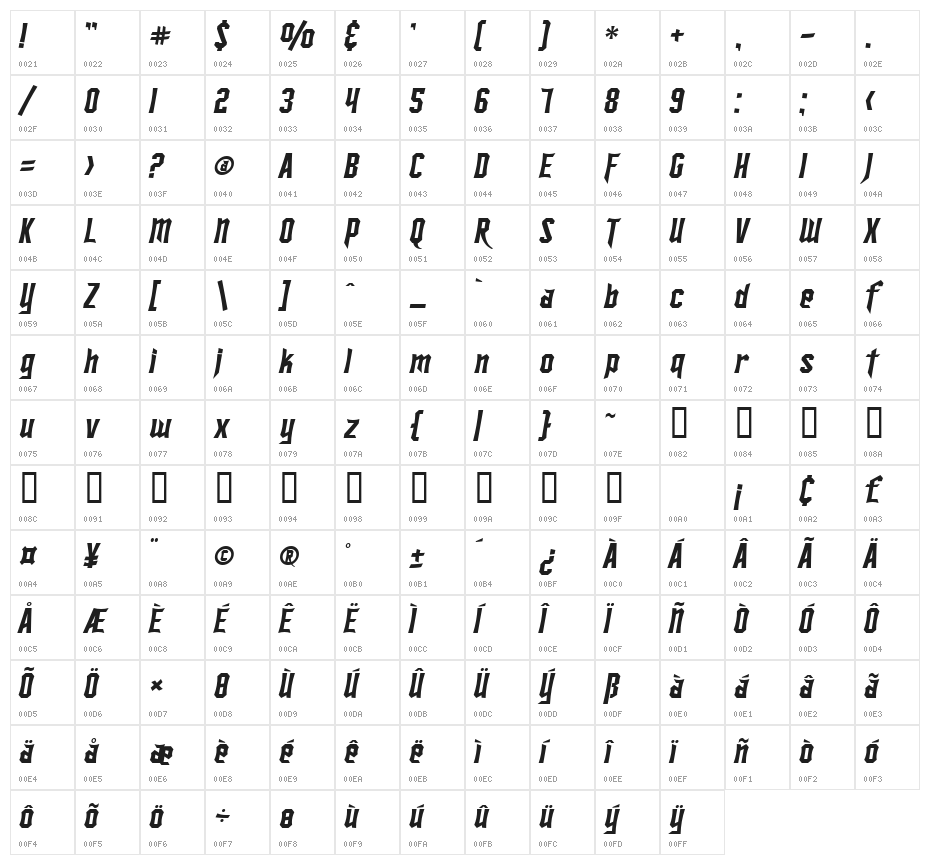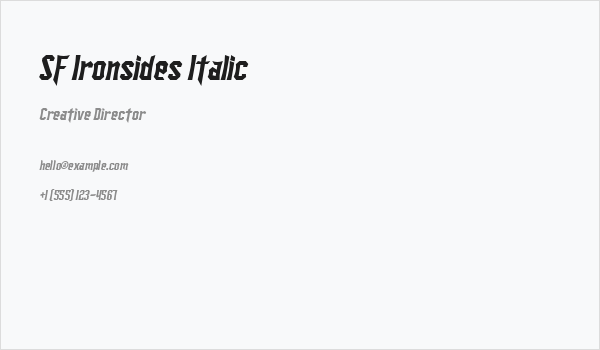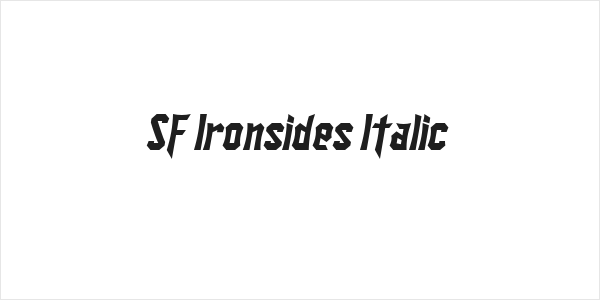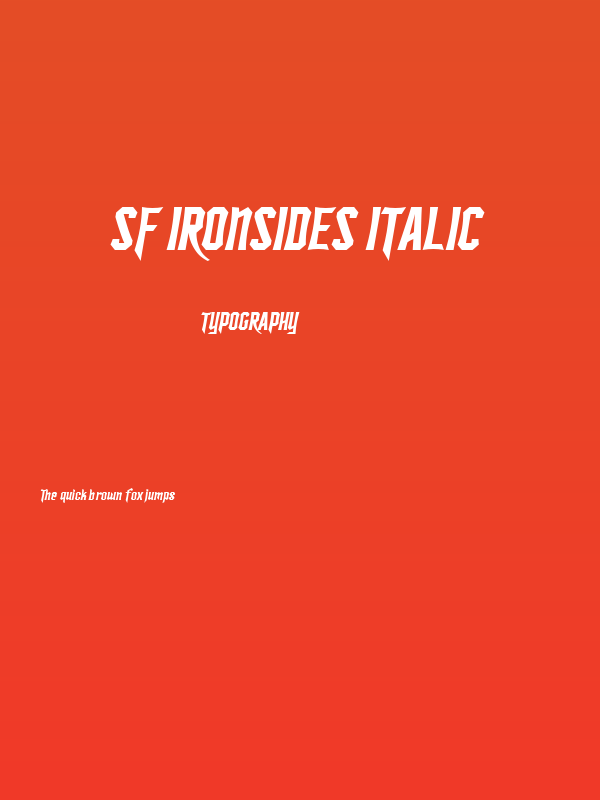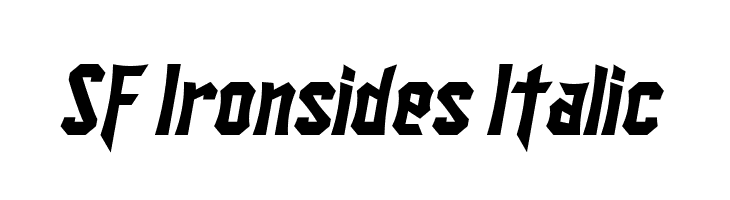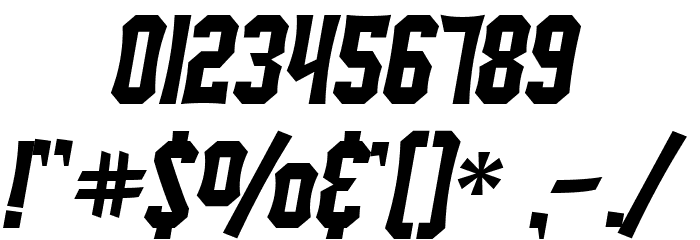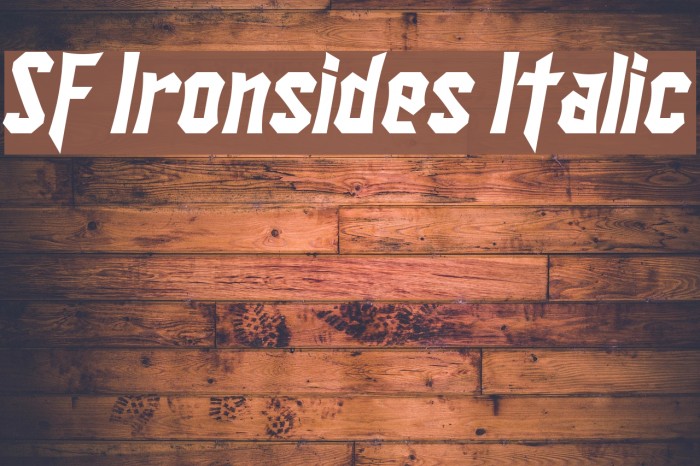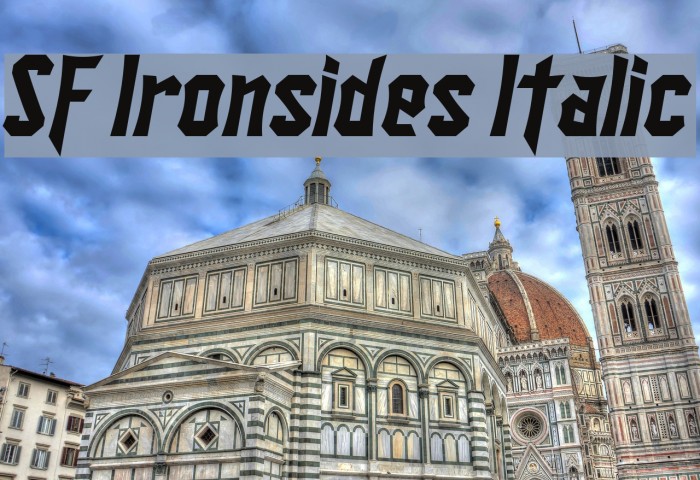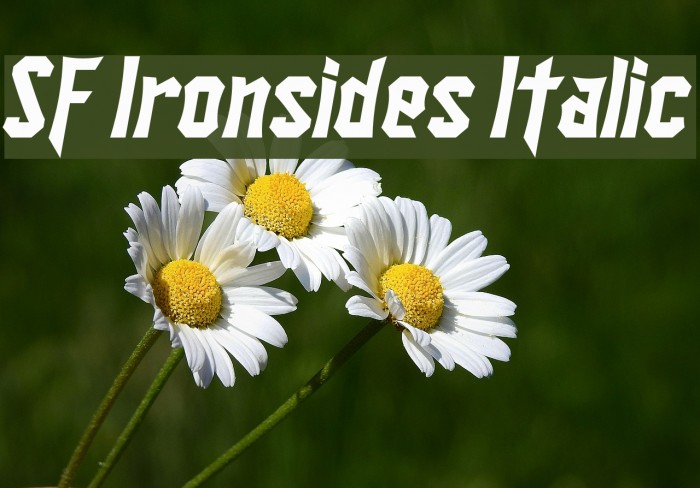
SF Ironsides Italic Font
✎ Serif
| Kategorien | Serif |
| Gesamtstil | Modern, Futuristic |
| Vorgeschlagene Projekte | Ideal for use in video game titles, movie posters, branding for tech companies, or any project needing a bold, futuristic look. |